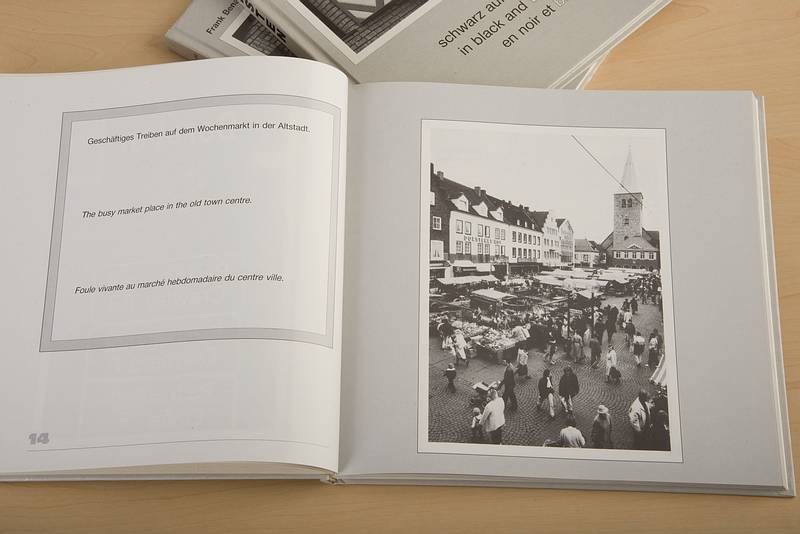
Dreisprachiger Satz für Bildband
ich muss für einen Bildband die Texte in deutscher, englischer und serbo-kroatischer Sprache setzen (lateinische Schrift).
Bei zweisprachigen Büchern wird die zweite Schrift meistens kursiv gesetzt, was mir nicht gefällt, da ich grundsätzlich keine Kursivschriften mag.
Welche Möglichkeiten sind sinnvoll zur optischen Unterscheidung von drei Sprachen? Derzeit denke ich daran, stets die gleiche Schrift zu nehmen, aber deutsch in 100 % schwarz, englisch in 70 % schwarz und serbo-kroatisch evtl. in grau-blau oder dunkelblau. Oder die beiden Fremdsprachen jeweils in leicht abweichenden Grautönen, evtl. sogar angepasst an das Bildmotiv? Oder wird das zu bunt? Oder …?
Eine weitere Differenzierung böten unterschiedliche Schriftschnitte, beziehungsweise – bei einer Schriftsippe – die unterschiedlichen Mitglieder derselben: Serif, Sans und Slab.
Einfach alles im gleichen Stil setzen, in konstanter Anordnung (z.B. nebeneinander). Der Leser merkt dann schon, was was ist.
Das wäre in der Tat die grafisch ansprechendste Variante. Man könnte, wenn man es noch etwas eindeutiger haben möchte, den jeweiligen Namen der Sprache über die Textblöcke setzen oder ein kleines Flaggensymbol, das sind gelernte Strukturen für mehrsprachige Texte. Und falls es eine Hauptsprache gibt und zwei, die in ihrer Wichtigkeit nachgeordnet sind, dann könnte man erstere etwas kräftiger setzen als die anderen beiden.
Eine weitere Differenzierung böten unterschiedliche Schriftschnitte, beziehungsweise – bei einer Schriftsippe – die unterschiedlichen Mitglieder derselben: Serif, Sans und Slab.
Das habe ich mal versucht, aber auf die Schnelle (viel Zeit hatte ich dafür nicht) keine Familien gefunden, deren Mitglieder hinreichend eigenständig erschienen. Zwei Mitglieder erschienen beim ersten Blick auf nebeneinander angeordnete Absätze einander immer ähnlicher als das dritte irgendeinem der beiden. Also es wirkte immer irgendwie A ——— B — C statt des angestrebten Eindrucks A —— B —— C. Drei gleichberechtigt, selbstständig nebeneinander stehende Sprachen zu repräsentieren, hat so m.E. jedenfalls nicht funktioniert.
Am nächsten kam übrigens noch die Kombination Museo Slab — Museo — Museo Sans, nur war dort das Problem, dass der Kontrast zwischen den drein generell zu gering war.
Einfach alles im gleichen Stil setzen, in konstanter Anordnung (z.B. nebeneinander). Der Leser merkt dann schon, was was ist.
Das dachte ich auch, wurde dann aber eines besseren belehrt. Anscheinend gibt es viele Leser, die nur den ersten Satz, den sie auf einer Seite finden, überfliegen und, falls er in einer fremden Sprache verfasst ist, komplett abbrechen und nicht weiter suchen.
Mir ist einmal das Problem untergekommen, Arbeitsbeispiele für »grinding machines«, viersprachig (deutsch, englisch, französisch, russisch) zu gestalten … was letzlich über das Layout gelöst wurde. Ein A4-Blatt mit einer technischen Zeichnung pro Seite, vorn zwei Sprachen, auf der Rückseite die nächsten zwei, die Abbildung, auf die sich die Erläuterungen/Tabellen bezogen, war vor- wie rückseitig identisch. Wenn man es niederschreibt, klingt es etwas umständlich, das (visuelle) Ergebnis war aber recht überzeugend.
Das hängt auch ein wenig vom Raum ab, der dem Text gegeben wird.
Bei diesem Beispiel hätte ich die drei Sprachen unterschiedslos gesetzt, weil sie sich durch den Weißraum klar abgrenzen:
Auch hier wären die drei Sprachen auch ohne unterschiedliche Schnitte o.ä. klar abgegrenzt, wenn sich das durch den Bildband durchzieht:
Wer einen dreisprachigen Bildband anschaut, wird normalerweise ja nicht von den drei Sprachen überrascht werden. Ich denke, die beste Lösung ist, die Gestaltung entsprechend aufzubauen.
Kannst du ein unverfängliches Beispiellayout deines Bildbandes zeigen?
Das hängt auch ein wenig vom Raum ab, der dem Text gegeben wird.
Bei diesem Beispiel hätte ich die drei Sprachen unterschiedslos gesetzt, weil sie sich durch den Weißraum klar abgrenzen:
Auch hier wären die drei Sprachen auch ohne unterschiedliche Schnitte o.ä. klar abgegrenzt, wenn sich das durch den Bildband durchzieht:
Wer einen dreisprachigen Bildband anschaut, wird normalerweise ja nicht von den drei Sprachen überrascht werden. Ich denke, die beste Lösung ist, die Gestaltung entsprechend aufzubauen.
Kannst du ein unverfängliches Beispiellayout deines Bildbandes zeigen?
Layout habe ich noch nicht, aber ich stelle es später gerne zur Diskussion vor.
Mein derzeitiger Stand:
Verschiedene Schriften (serif, sans-serif, slab-serif) scheiden für mich aus, das wirkt mir nebeneinander zu unruhig.
Kurz und gut: ich fände es schon schön, ein paar (typo)grafische Mittelchen im Werkzeugkoffer zu haben, um solchen Situationen ggf. zu entschärfen.